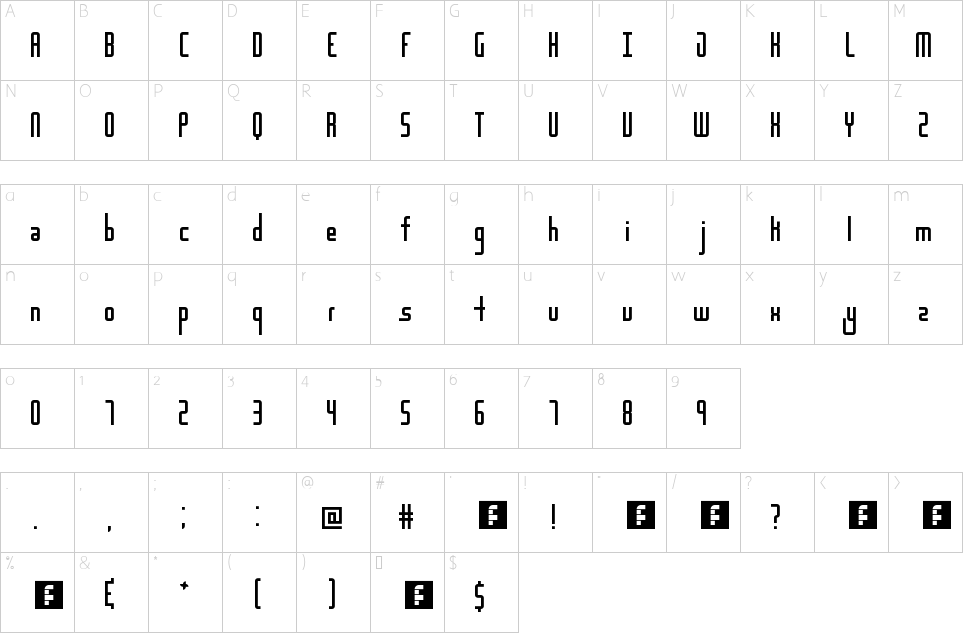
Aproveite a descoberta de uma nova fonte para seus projetos digitais com Destiny Font, disponível agora gratuitamente tanto para Windows quanto para Mac. Esta elegante e sofisticada fonte foi criada pelo designer desconhecido Geronimo Fonts, já baixada 4.956 vezes pela comunidade digital. Se você busca uma fonte moderna que possa dar um toque único a seus textos em projetos de design gráfico ou até mesmo em criações digitais pessoais, Destiny Font é definitivamente o item para você. Seu estilo clean e distinto se adequará perfeitamente aos ambientes de design onde deseja uma aparência atraente e minimalista. Para quem está sempre buscando novas opções de fontes gratuitas, não há melhor maneira de começar do que adquirir Destiny Font hoje. Não deixe de aproveitar o excelente trabalho de Geronimo Fonts e sua escolha para complementar sua biblioteca personalizada de recursos digitais.